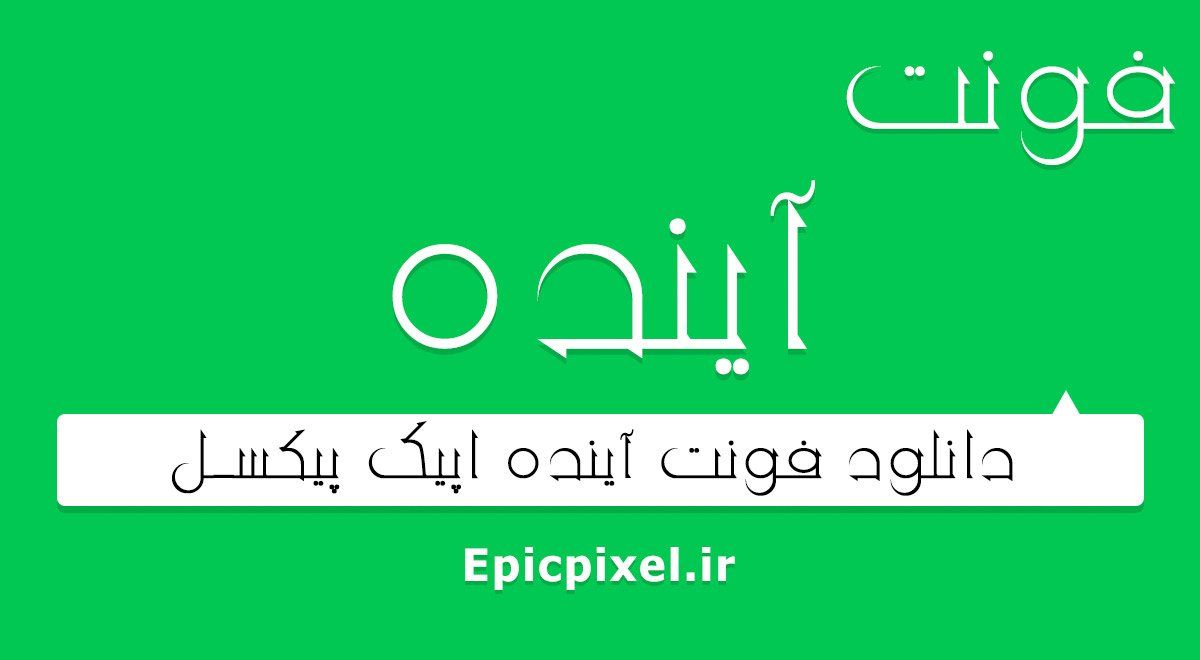
3 فونت آینده فارسی Ayandeh
فونت فارسی آینده، یک قلم فانتزی با طراحی خاص است که به صورت رایگان قابل دانلود می باشد. این فونت با پشتیبانی از تمام حروف و اعداد فارسی، در سه نسخه مختلف با ظاهری کاملاً یکسان (F Ayandeh, W Ayandeh, Mj_Future) ارائه شده است. فونت آینده دارای وزن نازک بوده و با توجه به استفاده از فونت های نازک در طراحی های مدرن، گزینه ای مناسب برای این سبک محسوب می شود. این قلم زیبا برای استفاده در انواع طراحی ها، متون، و به ویژه ساخت لوگوتایپ های خاص با وزن نازک کاربرد دارد و در انواع نرم افزارهای گرافیکی و روی موبایل قابل استفاده است.
قلمی نازک و فانتزی برای طراحی های مدرن
فونت فارسی آینده، یک قلم با ویژگی های بصری متمایز و کاربردی برای طراحان است. این فونت از سری فونت های فانتزی فارسی محسوب شده و دارای طراحی خاصی می باشد که آن را از فونت های معمولی جدا می کند و جلوه ای منحصربه فرد به متن می بخشد. این طراحی، فونت آینده را برای پروژه هایی با نیاز به حس خلاقیت و سبکی ویژه مناسب می سازد.
یکی از نکات قابل توجه در خصوص فونت آینده، ارائه آن در سه نسخه مختلف با ظاهری کاملاً یکسان است. این نسخه ها با نام های F Ayandeh, W Ayandeh, و Mj_Future در دسترس هستند. هرچند این نسخه ها ممکن است تفاوت های فنی جزئی در ساختار فایل داشته باشند، اما از نظر ظاهری فونت یکسانی را ارائه می دهند که این امکان انتخاب بین نسخه های مختلف را برای سازگاری یا نیازهای فنی خاص فراهم می کند.
فونت آینده دارای وزن نازک است. در حالی که عموماً طراحان گرافیک برای جلب توجه بیشتر به دنبال فونت هایی با وزن ضخیم هستند، در طراحی های مدرن از فونت های نازک نیز به فراخور نیاز طرح و برای ایجاد تعادل بصری، القای حس ظرافت، مینیمالیسم یا سبکی ویژه استفاده می شود. فونت آینده با وزن نازک خود، گزینه ای عالی برای این سبک از طراحی ها محسوب می شود و می تواند حس مورد نظر را به خوبی منتقل کند.
دانلوداین قلم بسیار متنوع است و می توانید از آن در انواع طراحی ها و برای انواع متون استفاده کنید. از طراحی های چاپی گرفته تا محتوای دیجیتال. فونت آینده با وزن نازک خود، به صورت ویژه برای استفاده در لوگوتایپ های خاص که نیاز به ظاهری ظریف و متمایز دارند و می خواهند از سنگینی فونت های بولد فاصله بگیرند، کاربرد دارد. این فونت برای خلق طراحی های زیبا در زمینه های مختلف مناسب است و پتانسیل بالایی برای خلاقیت ارائه می دهد.
از نظر پشتیبانی زبانی، فونت آینده دارای تمام حروف و اعداد فارسی است که امکان استفاده کامل از آن را در محتوای فارسی بدون هیچ نقصی فراهم می کند و آن را به ابزاری کاربردی برای طراحان فارسی زبان تبدیل می کند. این فونت فانتزی قابل استفاده در انواع نرم افزارهای گرافیکی است؛ چه بر روی سیستم های دسکتاپ حرفه ای و چه بر روی ابزارهای موبایل. این ویژگی، دست طراحان را برای استفاده از آن در محیط های کاری مختلف، از دسکتاپ تا موبایل، باز می گذارد.
کاربردهای فونت آینده در طراحی گرافیک
با توجه به وزن نازک، طراحی خاص و فانتزی، و پشتیبانی از تمام حروف و اعداد فارسی، فونت آینده کاربردهای متنوعی در طراحی گرافیک دارد و برای خلق آثاری با جلوه ای ظریف و مدرن مناسب است. این قلم به طور کلی قابل استفاده در انواع طراحی ها و برای انواع متون است. به صورت ویژه برای استفاده در طراحی های زیبا با سبک مدرن که از فونت های نازک بهره می برند، و همچنین برای ساخت لوگوتایپ های خاص با وزن نازک مناسب می باشد و می تواند هویتی بصری متمایز به برندها ببخشد. این فونت در انواع نرم افزارهای گرافیکی دسکتاپ و موبایل قابل استفاده است و برای تولید محتوای بصری، طراحی بنرها و پوسترها، و المان های گرافیکی با جلوه ای ظریف و فانتزی کاربرد دارد.